Tổng Hợp Font Chữ Việt Nổi Tiếng: VNI, TCVN3 và Unicode
Bộ font này đảm bảo khả năng tương thích tối đa. Dù máy tính của bạn đang sử dụng công cụ gõ tiếng Việt nào, bạn vẫn có thể dễ dàng hiển thị và sử dụng các font chữ này.
Việc tích hợp cả ba bộ font chữ quan trọng này giúp giải quyết triệt để vấn đề hiển thị ký tự tiếng Việt không chính xác, đặc biệt khi mở các tài liệu cũ hoặc truy cập các trang web sử dụng các bảng mã khác nhau.
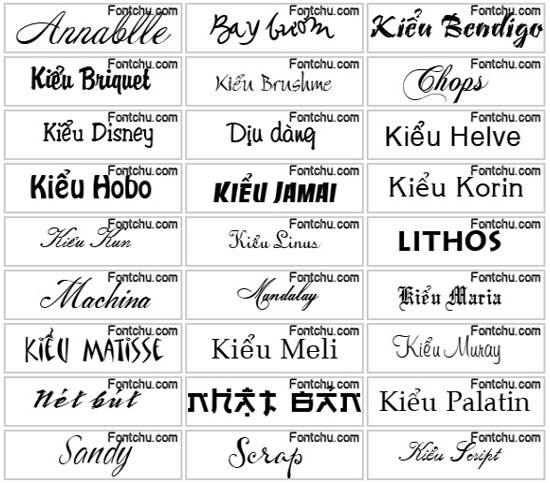
Với bộ font chữ này, người dùng có thể yên tâm về việc hiển thị tiếng Việt một cách chính xác và đầy đủ trên mọi ứng dụng và nền tảng.
Khám phá những tính năng ưu việt của bộ font VNI - TCVN3 - Unicode
Bộ font này cung cấp khả năng hỗ trợ đa dạng các bảng mã tiếng Việt, bao gồm TCVN3, VNI và Unicode. Nhờ đó, người dùng có thể dễ dàng tương tác với các văn bản cũ, cũng như chuyển đổi giữa các định dạng khác nhau một cách thuận tiện.
Khả năng tương thích vượt trội
Bộ font tương thích tốt với các công cụ gõ tiếng Việt phổ biến hiện nay như Unikey và Vietkey. Điều này đảm bảo quá trình nhập liệu tiếng Việt diễn ra chính xác và hiệu quả, giúp người dùng tiết kiệm thời gian và công sức.
Đảm bảo hiển thị văn bản chính xác
Sử dụng bộ font này giúp đảm bảo rằng văn bản tiếng Việt sẽ được hiển thị một cách chính xác trên nhiều hệ thống và phần mềm khác nhau. Điều này giúp giảm thiểu tối đa tình trạng lỗi font hoặc mất dấu, mang lại trải nghiệm đọc tốt hơn cho người dùng.
Font VNI, TCVN3-ABC và Unicode: Những lựa chọn đa dạng
Font VNI là một trong những bộ font chữ tiếng Việt lâu đời và được sử dụng rộng rãi. Chúng thường được ứng dụng trong các lĩnh vực như văn phòng, thiết kế đồ họa và in ấn.
Bên cạnh đó, font TCVN3-ABC là bộ font tiếng Việt được chuẩn hóa theo bảng mã TCVN3. Đây là lựa chọn lý tưởng cho những ai thường xuyên làm việc với các tài liệu cũ hoặc các hệ thống yêu cầu bảng mã này.
Cuối cùng, font Unicode là chuẩn mã quốc tế, cho phép hiển thị tiếng Việt và nhiều ngôn ngữ khác. Các font Unicode phổ biến như Arial, Times New Roman và Calibri đều hỗ trợ tiếng Việt một cách hoàn hảo.
Vai trò của các bộ font trong việc bảo mật và tương thích
Các bộ font VNI, TCVN3 và Unicode đóng vai trò quan trọng trong việc thể hiện chữ viết tiếng Việt trên máy tính. Tuy nhiên, cơ chế bảo mật của chúng không phải là một tính năng được thiết kế riêng biệt, mà chủ yếu dựa vào việc quản lý quyền truy cập và sử dụng của hệ điều hành và phần mềm.
Đối với font VNI và TCVN3, do tính chất mã hóa phông chữ theo chuẩn riêng, nếu không có font tương ứng được cài đặt trên hệ thống, văn bản có thể hiển thị sai hoặc bị lỗi. Điều này gián tiếp bảo vệ nội dung khi chia sẻ, nhưng cũng có thể làm giảm tính tương thích.
Trong khi đó, Unicode được xây dựng như một chuẩn mã hóa quốc tế thống nhất, giúp tăng cường tính bảo mật và tương thích khi trao đổi dữ liệu trên nhiều nền tảng. Bảo mật trong Unicode phụ thuộc vào các lớp bảo mật của hệ thống và ứng dụng, bao gồm mã hóa dữ liệu, quản lý quyền truy cập và các cơ chế bảo vệ dữ liệu như DRM hoặc chữ ký số.